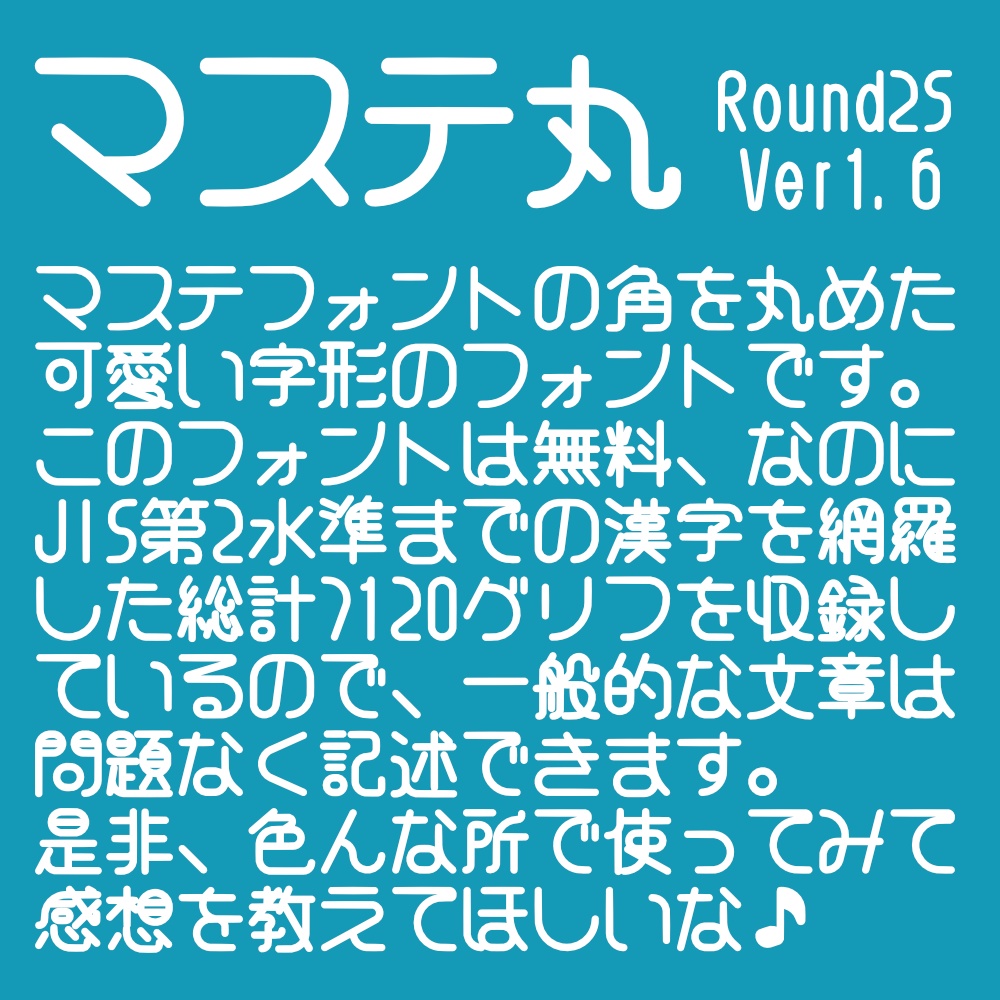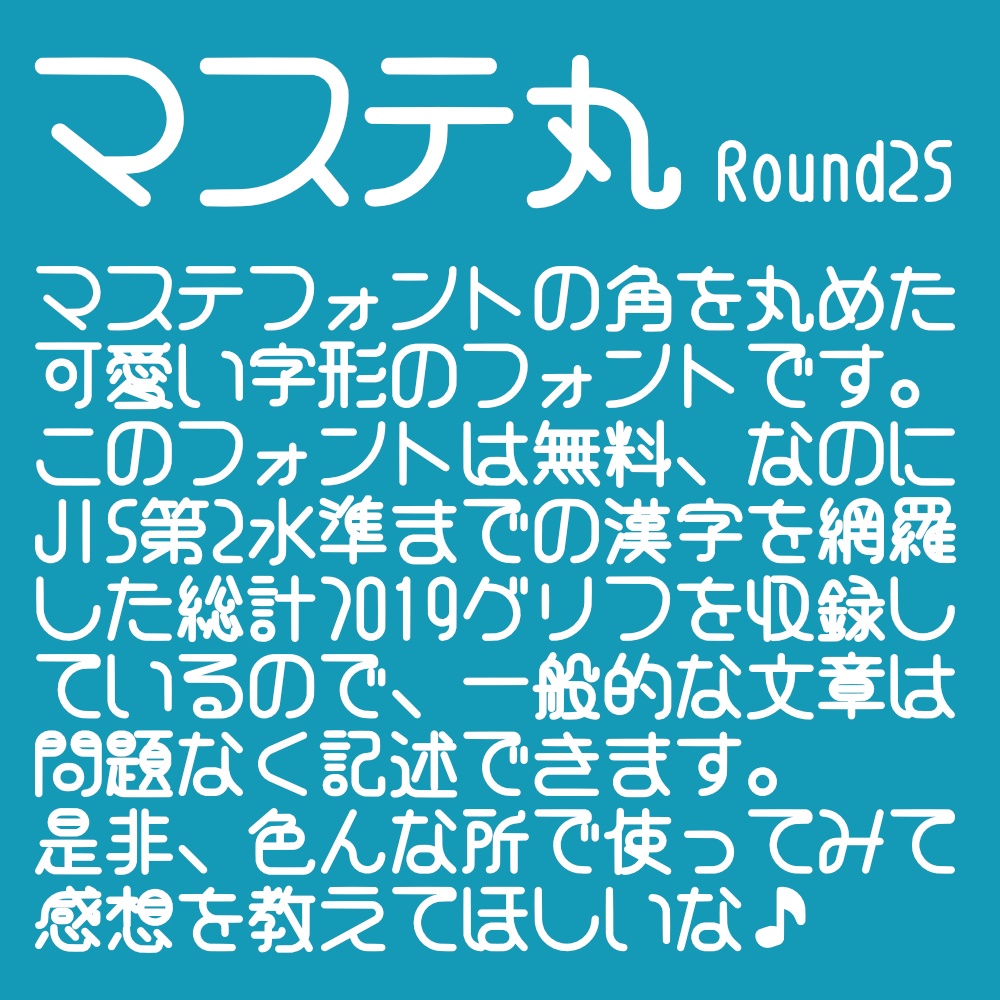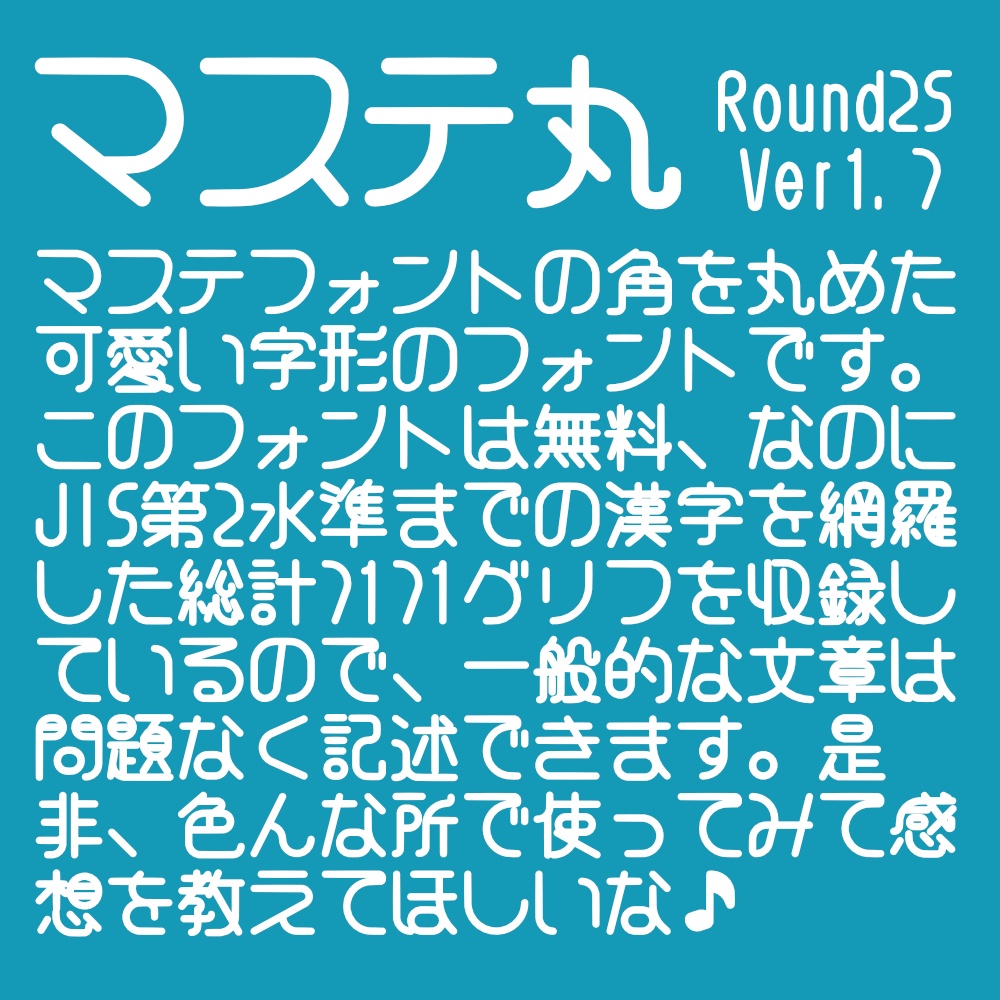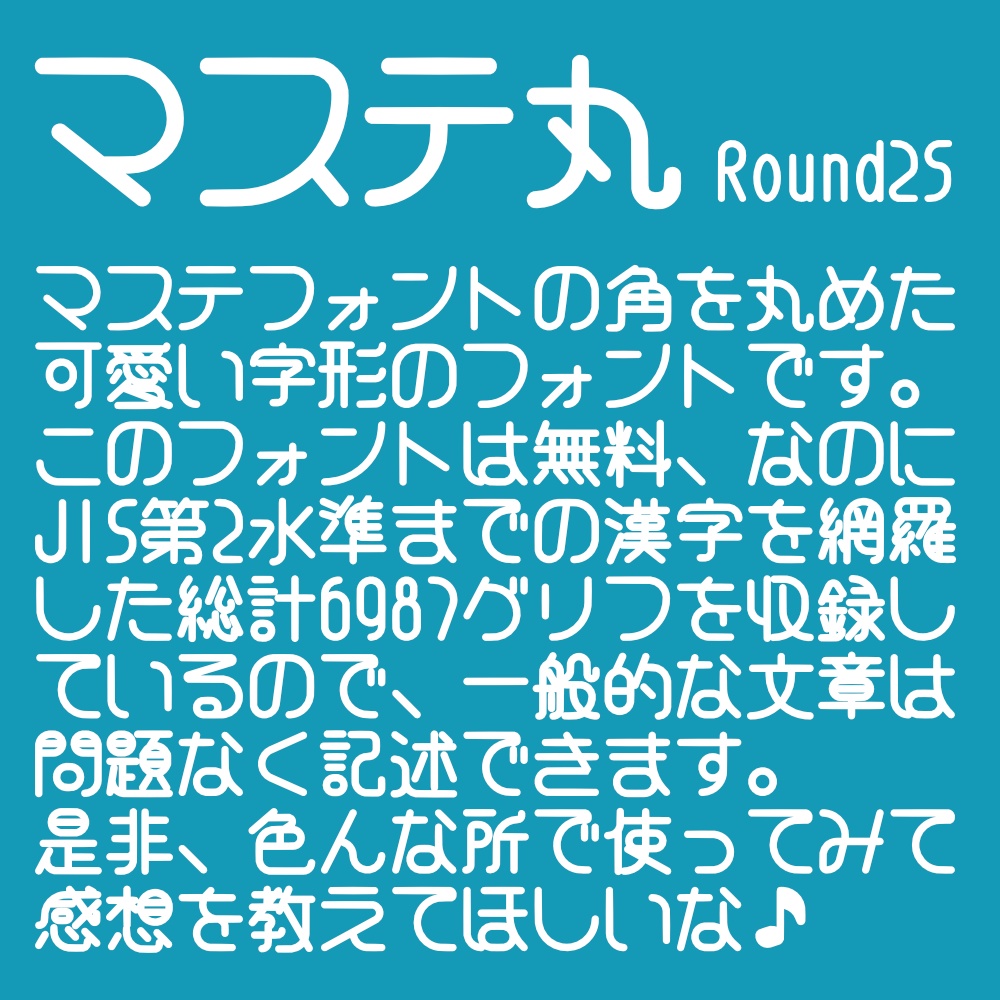
フォント マステ丸 ラウンド25
マステフォントをベースとし、全ての角に丸めた可愛らしい字形のフォントです。 JIS第2水準までの漢字を網羅し、総計7120グリフを収録しています。 <<< [スキ!]数400突破記念! ロシア語アルファベットを追加しました! >>> <<< [スキ!]数300突破記念! ローマ数字を追加しました! >>> <<< [スキ!]数200突破記念! 罫線(基本)を追加しました! >>> <<< [スキ!]数100突破記念! ギリシャ文字を追加しました! >>>